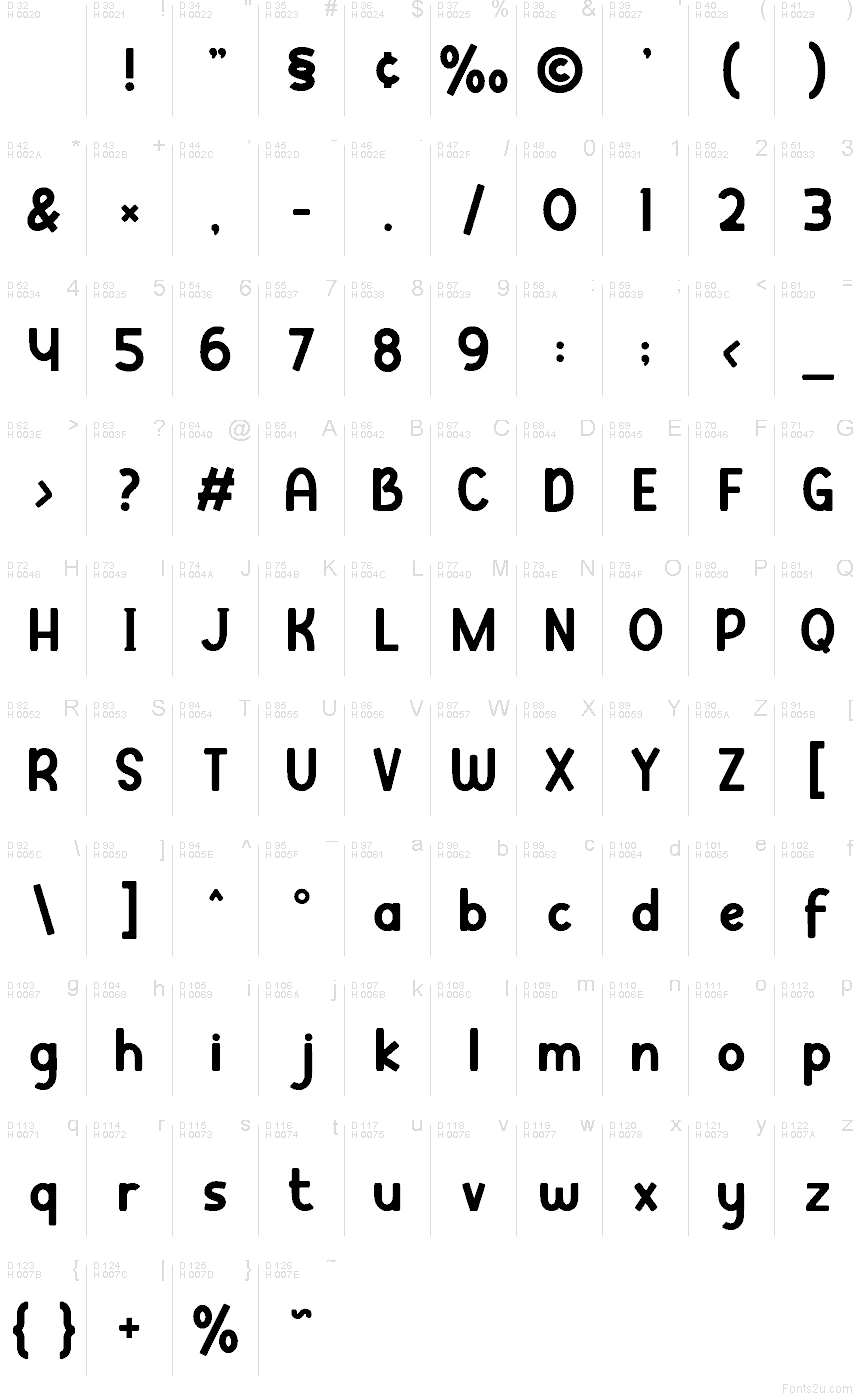
Clever Science
Clever Science von Putracetol Studio ist eine kostenlose Cartoon-Display-Schriftart mit großen, abgerundeten Buchstaben und einer fröhlichen, verspielten Ausstrahlung, die an Schulprojekte erinnert. Ihre kräftigen Striche, weichen Ecken und schwungvollen Kleinbuchstaben verleihen dem Alphabet eine freundliche, fast knetgummiartige Anmutung, die eher auf Spaß als auf formale Strenge setzt.
Diese kostenlose Schriftart eignet sich hervorragend für Kinderbuchcover, Klassenzimmer-Poster, Grafiken für wissenschaftliche Projekte, Sticker-Verpackungen und lebhafte YouTube-Titel, bei denen ein fett gesetztes Wort nahbar und sympathisch wirken soll. Sie funktioniert auch bestens für kurze Überschriften und logotypische Wortmarken, da die Buchstaben kompakt und einfach genug gestaltet sind, um visuell gut zusammenzuhalten, während sie gleichzeitig diesen animierten, handgezeichneten Charme bewahren.